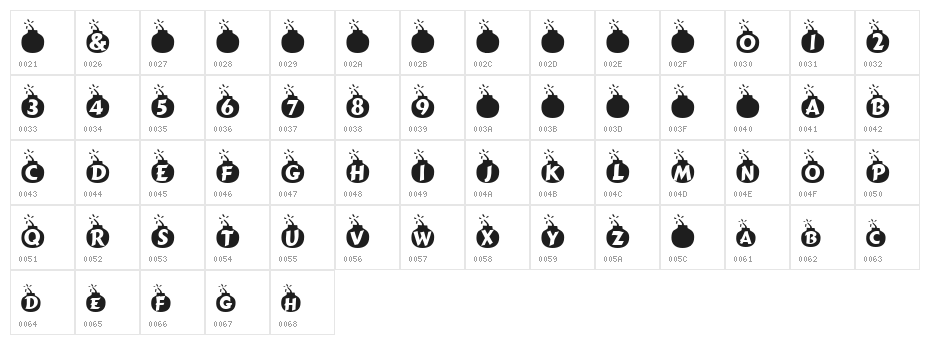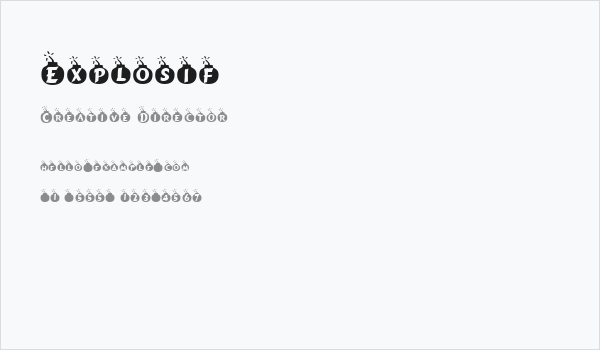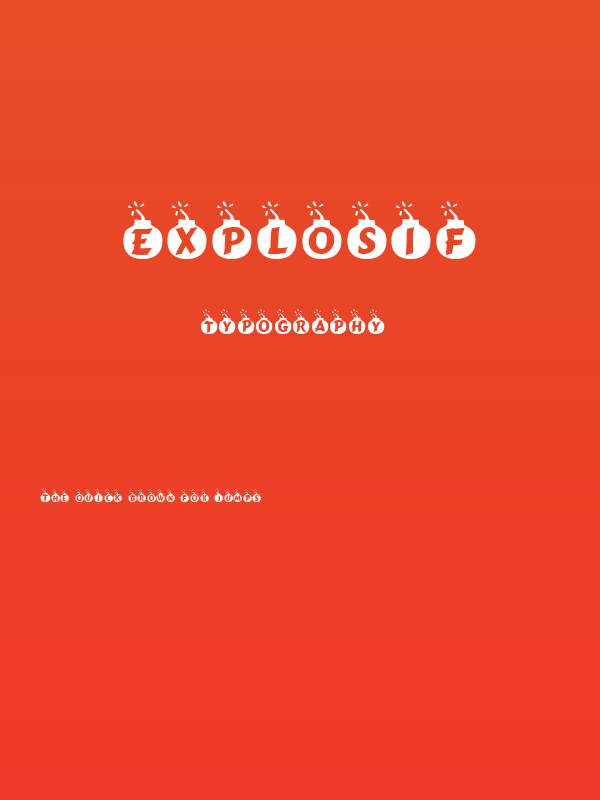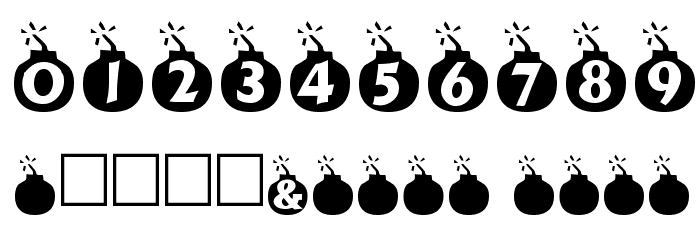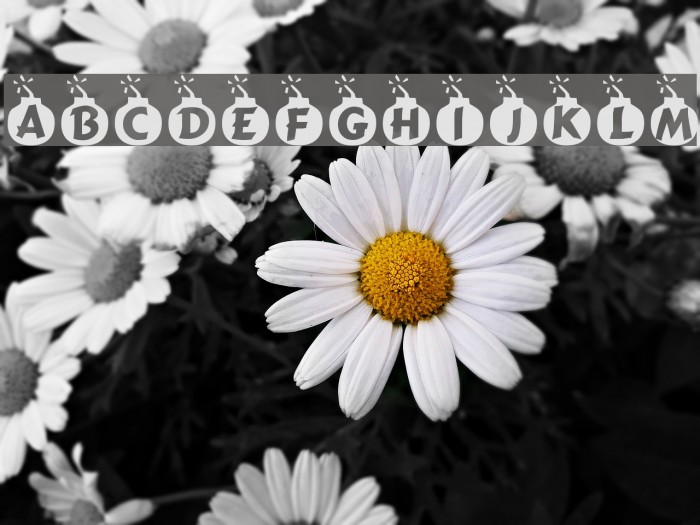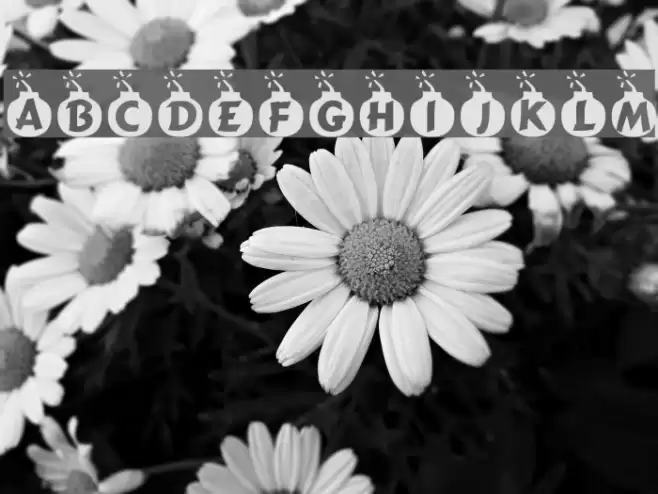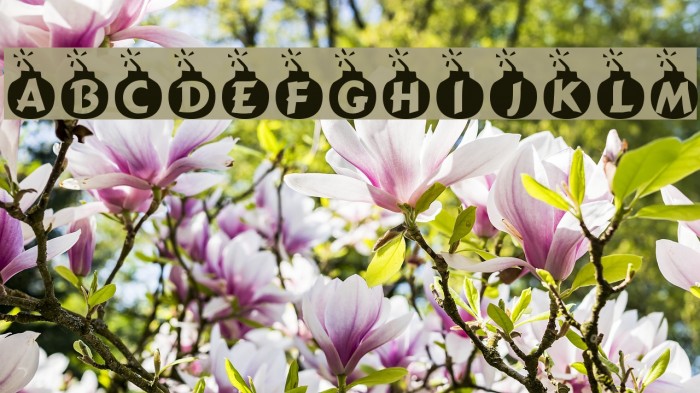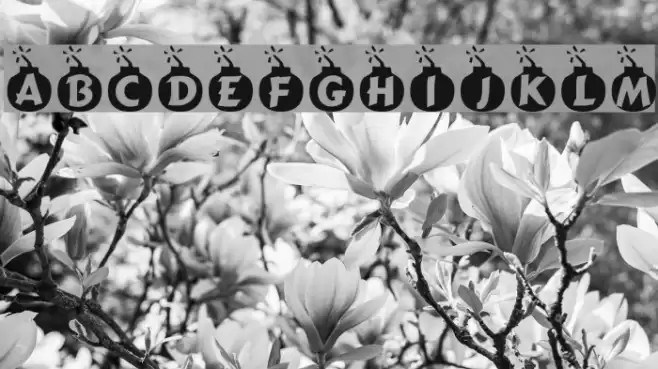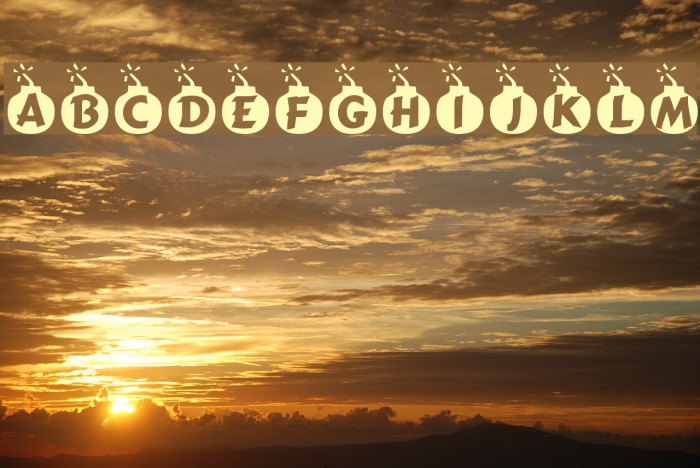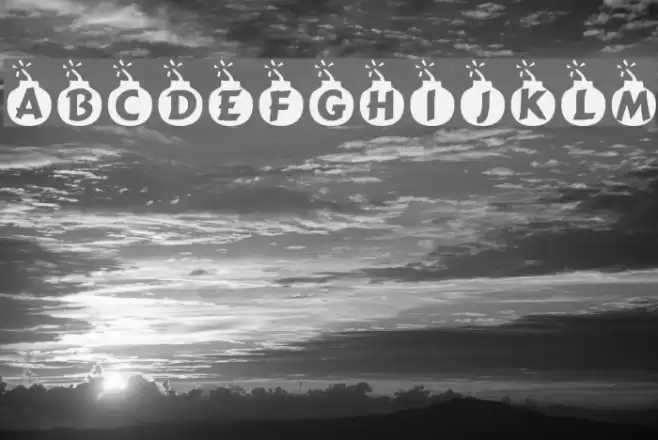
Explosif Font
✎ Decorative
| مشاريع مقترحة | Ideal for comic book titles, video game graphics, party invitations, and any project needing a fun, explosive theme. |